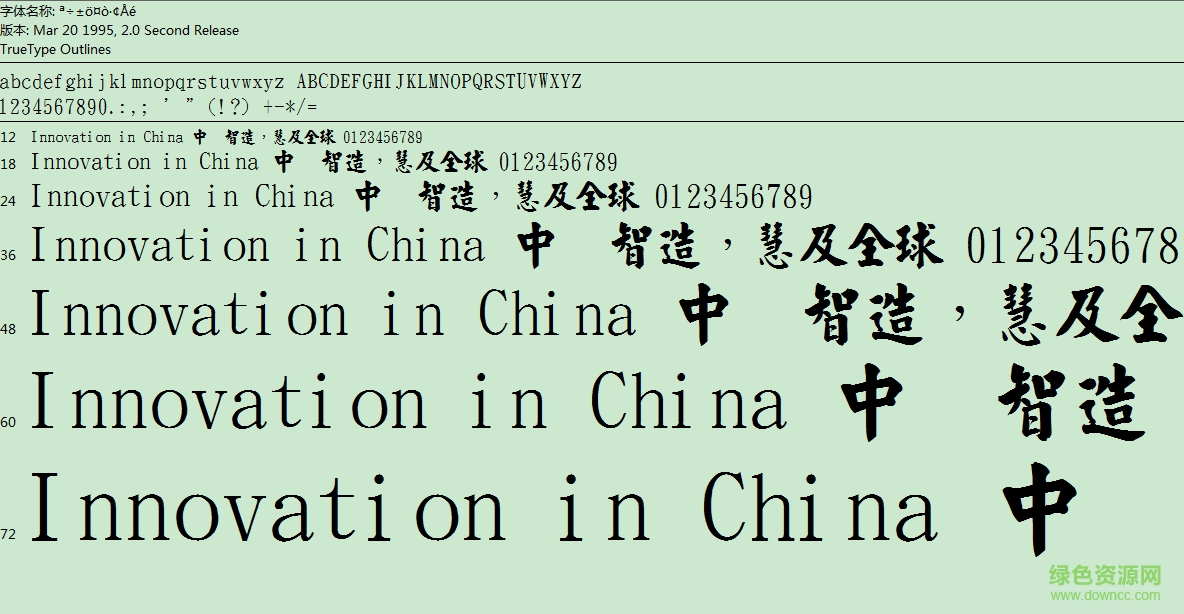
经典毛楷简体字体
经典简毛楷字体是小编为大家搜集的经典繁毛楷相似简体字,字形端正,粗而不重,流畅洒脱,张力十足,喜欢这款字体的小伙伴赶紧来绿色资源网下载收藏吧!
经典简毛楷字体特点
这款字体融合了毛笔字的特点,展示了一种粗犷之感,字体为楷书字体,微粗,非常的漂亮,实用性非常的广
经典简毛楷体
很美的字体